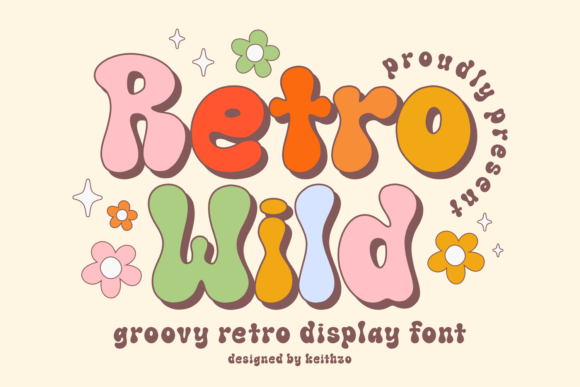
Tipografía de exhibición Funk psicodélico y salvaje retro
Retro Wild es una encantadora fuente de exhibición diseñada con curvas de inspiración vintage y una estética retro relajada. Sus letras tienen un aspecto suave y nostálgico, ideal para diseños que buscan calidez, personalidad y un aire retro. Ya sea que crees ropa, impresiones para decoración del hogar o gráficos digitales, Retro Wild hace que tus diseños destaquen con su distintivo carácter retro.
Por qué te encantará
Retro Wild aporta nostalgia y calidez a tus diseños, a la vez que es versátil y fácil de usar en múltiples plataformas. Sus suaves curvas retro la hacen especialmente adecuada para diseños amigables y accesibles de marca, ropa y estilo de vida. Al ser una fuente gratuita, es una forma económica de realzar tus proyectos sin arriesgarte a gastos adicionales: perfecta tanto para aficionados, creadores DIY como para pequeños comercios.
| Estilo / Vibra | Curvas retro suaves, exhibición cálida de estilo vintage. | Pantalla moderna y minimalista | Exhibición retro áspera o grunge |